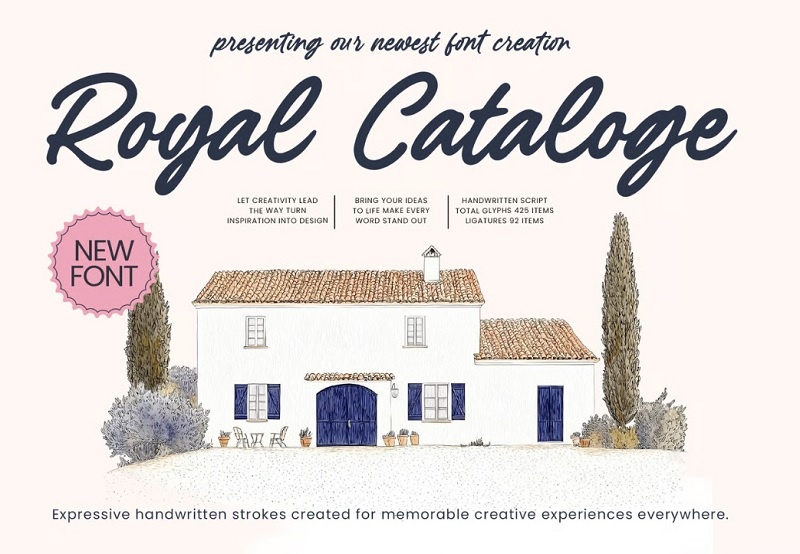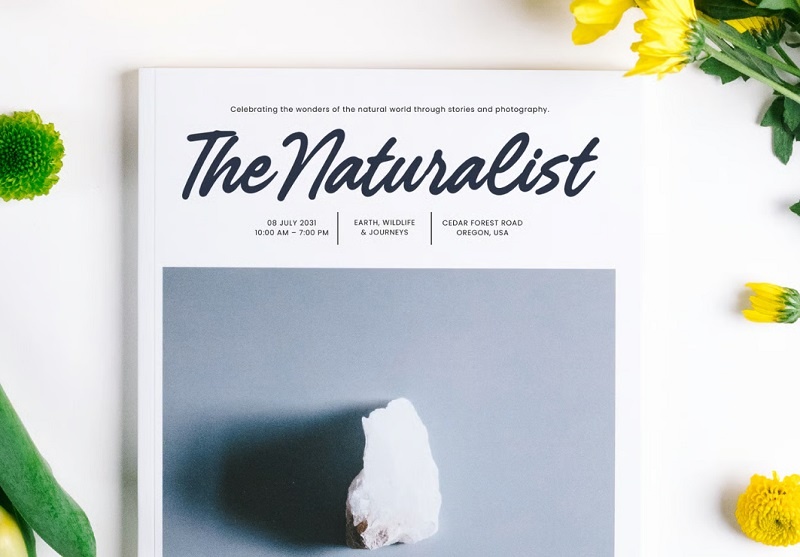
دانلود 14 فونت انگلیسی تحریری writing fonts
فونت انگلیسی تحریری
1- دانلود فونت انگلیسی تحریری و لوکس Tresno
Tresno writing fonts یک فونت انگلیسی تحریری و امضای لوکس است که به صورت اختصاصی در سایت جی اف ایکس دانلود قرار داده شده است. فونت انگلیسی تحریری ساخته شده با دست نوشته های طبیعی، فونت طراحی شما را زیباتر و شیک تر می کند. این فونت انگلیسی پیوسته برای هر طراحی زیبا مانند امضا، واترمارک، لوگوی شخصی یا شرکتی، نام تجاری، نقل قول و غیره مناسب است.
✅ نام فونت انگلیسی : Tresno
✅ پشتیبانی از کاراکترهای چند زبانه
✅ ویژگی Opentype مانند Styistic Alternate و Standard Ligature
2- دانلود فونت تحریری انگلیسی برای فتوشاپ Marryliane Handwriting
یک فونت خط تحریری انگلیسی دست‌نویس مناسب برای وبلاگ‌نویسی، رسانه‌های اجتماعی، برندسازی، بسته‌بندی محصول، دعوت‌نامه عروسی، نام تجاری، سرفصل‌ها، علامت‌ها، برچسب‌ها، امضا، جلد کتاب، پوستر، نقل قول و موارد دیگر عالی است.
✅ پایه لاتین A-Z و a-z، جایگزین های a-z، اعداد،
✅ پشتیبانی چند زبانه Ligatures
3- فونت انگلیسی تحریری Karllina برای موبایل (اینشات) ، ویندوز و مک
شما می توانید با دانلود فونت انگلیسی تحریری Karllina از جی اف ایکس دانلود سطح کاری خودتان را ارتقاء دهید ! این فونت تحریری برای پروژه‌های برندسازی، لوگو، طرح‌های عروسی، پست‌های رسانه‌های اجتماعی، تبلیغات، بسته‌بندی محصول، طرح‌های محصول، برچسب، عکاسی، واترمارک، دعوت‌نامه، لوازم التحریر و هر پروژه‌ای که نیاز به سلیقه دست‌نویسی دارد، مناسب است.شما می توانید در تمامی برنامه های آفیس مانند Word ، اینشات ، فتوشاپ و ...از این فونت ها استفاده نمایید.اگر به دنبال مجموعه فونت های تحریری انگلیسی هستید این مجموعه فوق العاده از جی اف ایکس دانلود به شما پیشنهاد می شود.
4- دانلود فونت انگلیسی دست نویس تحریری با نام Bettyna
فونت Bettyna یکی دیگر از فونت های تحریری این مجموعه می باشد که به سبک دست نویس یا Handwriting است. شما می توانید در طراحی های مختلف کارت تبریک، دعوت عروسی، پوستر ها و سایر موضوعات دیگر از این فونت تحریری استفاده نمایید. این فونت دارای ویژگی open type می باشد و با 2 فرمت OTF و TTF برای دانلود قرار داده شده است. با تهیه این مجموعه جدیدترین فونت های انگلیسی تحریری را یک جا داشته باشید.
5- فونت خط تحریری انگلیسی Handwriting
Handwriting نام یک فونت خط تحریری انگلیسی به سبک امضا با طراحی حروف دست نویس و واقعی است. این فونت تحریری انگلیسی برای برندهای لوکس، لوگو زیبایی، مد، هنرمند، وبلاگ نویسی، رسانه های اجتماعی، دعوت نامه های عروسی، کارت ها، پوستر فیلم و موارد دیگر عالی است. شامل مجموعه ای کامل از حروف انگلیسی با حروف بزرگ و کوچک زرق و برق دار، نمادهای چند زبانه، اعداد، علائم نقطه گذاری و لیگاتورها است.
6- فونت خط تحریری انگلیسی Friend Write
Friend Write نام این فونت انگلیسی تحریری می باشد. یک فونت تحریری زیبا شامل مجموعه کامل از حروف بزرگ و کوچک، اعداد، و نقطه گذاری است. قابل استفاده در انواع نرم افزار های فتوشاپ، ایلوستریتور، ایندیزاین، ورد و ... می باشد.
7- فونت تحریری انگلیسی برای اندروید
Frethyna نام این فونت تحریری انگلیسی برای اندروید است. این فونت با سبک جذاب مناسب برای لوگو تایپوگرافی، نقل قول های چاپی، دعوت نامه ها، کارت ها، بسته بندی محصول، هدر، سربرگ، پوستر، طراحی پوشاک، برچسب و غیره عالی است. شامل فایل های OTF -TTF و WOFF می باشد. مناسب برای سیستم عامل مک و ویندوز و قابل استفاده در انواع نرم افزارهای فتوشاپ، ایلاستریتور و ... است.
8- فونت های انگلیسی تحریری و خوشنویسی جدید
این مطلب شامل 2 فونت انگلیسی تحریری زیبا می باشد. فونت‌های تحریری انگلیسی و خوشنویسی، با الهام از خط زیبای دست‌نوشته، به طراحی‌های شما روح و ظرافت خاصی می‌بخشند. از طراحی کارت ویزیت و لوگو گرفته تا پوستر و دعوت‌نامه، این فونت‌ها در طراحی‌های مختلف کاربرد دارند.
دانلود فونت تحریری جدید و حرفه ای با نام Just Write
9- فونت انگلیسی تحریری مناسب برای طراحی پوستر و کارت ویزیت
اگر به دنبال یک فونت انگلیسی تحریری مناسب برای طراحی پوستر و کارت ویزیت هستید، انتخاب فونت نقش مهمی در زیبایی و حرفه‌ ای شدن کار شما دارد. استفاده از فونت‌ های تحریری انگلیسی می‌تواند متن شما را با جلوه‌ ای دست‌نویس، هنری و جذاب نمایش دهد و به طراحی هویت منحصر‌ به‌ فردی ببخشد. این فونت‌ ها علاوه بر پوستر و کارت ویزیت، برای لوگو، بروشور، طراحی شبکه‌های اجتماعی و حتی کاور ویدیو نیز کاربرد زیادی دارند. یک فونت تحریری انگلیسی حرفه‌ای به نوشته‌ های ساده روح تازه می‌دهد و باعث می‌شود طرح شما در نگاه اول توجه مخاطب را جلب کند.